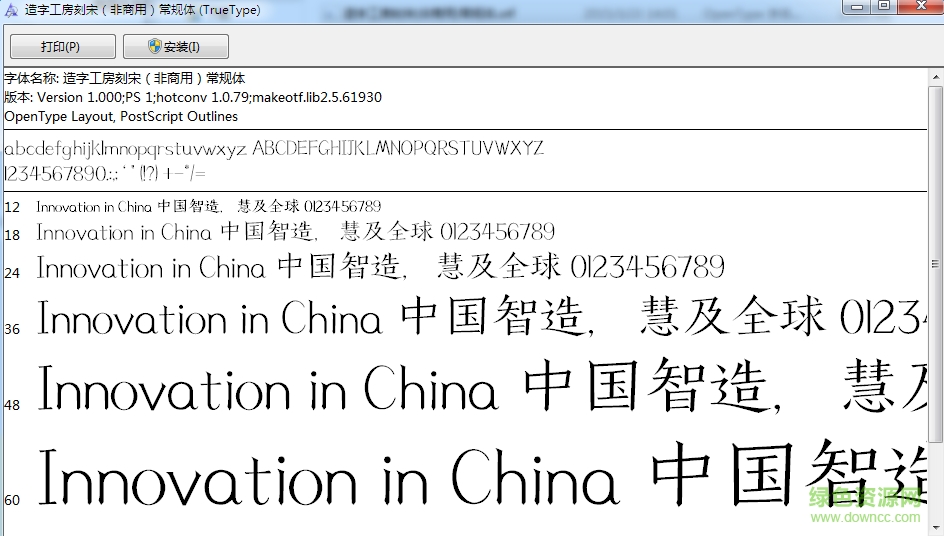
造字工房刻宋體是一款仿造古代刻板印刷字體改編而來的電腦字體,秉承原版字體造型秀美適意、剛?cè)岵?jì)的特點(diǎn),在正文表現(xiàn)與品牌宣傳上有很大的應(yīng)用空間,喜歡可以來綠色資源網(wǎng)下載試用!
造字工房刻宋體,秉承古籍木版印刷之字形特性,筆畫具刀刃之鋒美,且造型秀美適意、剛?cè)岵?jì),蘊(yùn)傳統(tǒng)宋體風(fēng)格特性,在傳統(tǒng)筆形間創(chuàng)新,結(jié)合當(dāng)代設(shè)計(jì)視覺環(huán)境,易讀性更強(qiáng)!